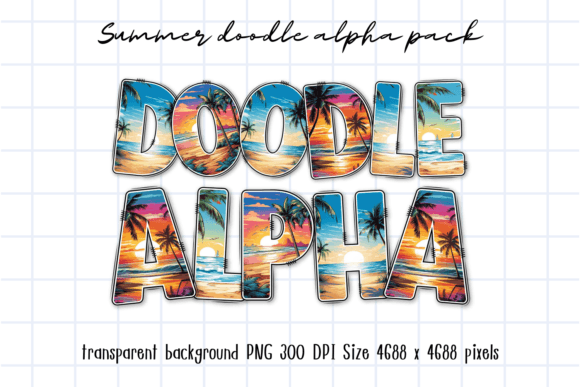
Summer Vacation Sea Beach Doodle Letters
Mencari elemen reka bentuk yang sesuai boleh menjadi mencabar, tetapi Summer Vacation Sea Beach Doodle Letters menawarkan koleksi luar biasa yang menaik taraf karya anda serta-merta.
Dicipta dengan ketepatan, Summer Vacation Sea Beach Doodle Letters menyediakan vektor yang bersih, tipografi yang licin dan lesen komersial untuk ketenangan fikiran.